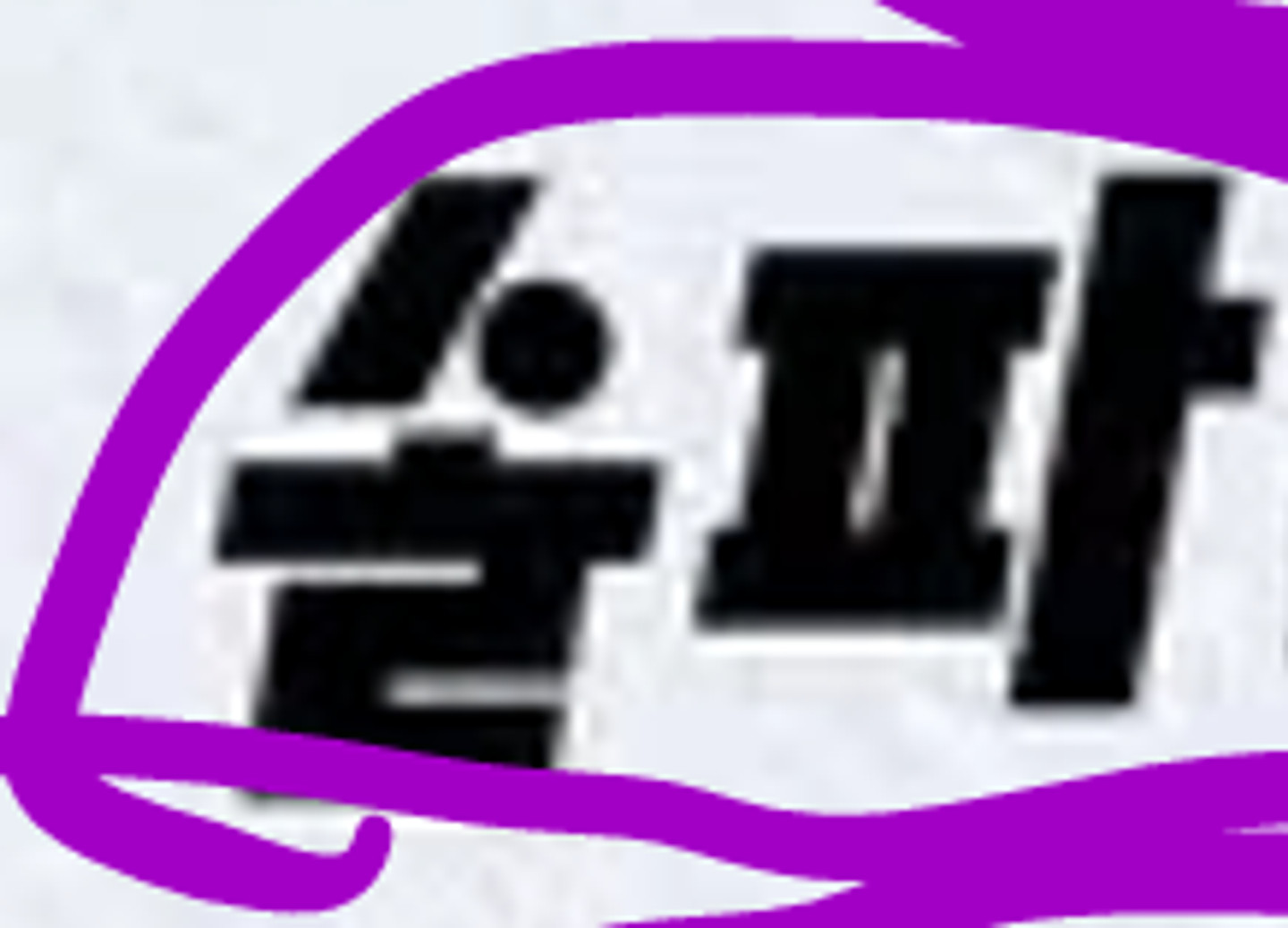
이 글씨체가 뭔지 알고 싶습니다. 필기체 편지체 비슷한것 다 찿아봤는데 비슷하긴 한데...못찿겠습니다....무슨 폰트인지 알려주세요..감사합니다.
꼭 이 폰트가 아니더라도, 저런 식으로 가로획이 얇고 획 끝 부분에 ▲느낌으로 처리가 되어있는 폰트가 있으면 소개해 주시면 감사하겠습니다!!